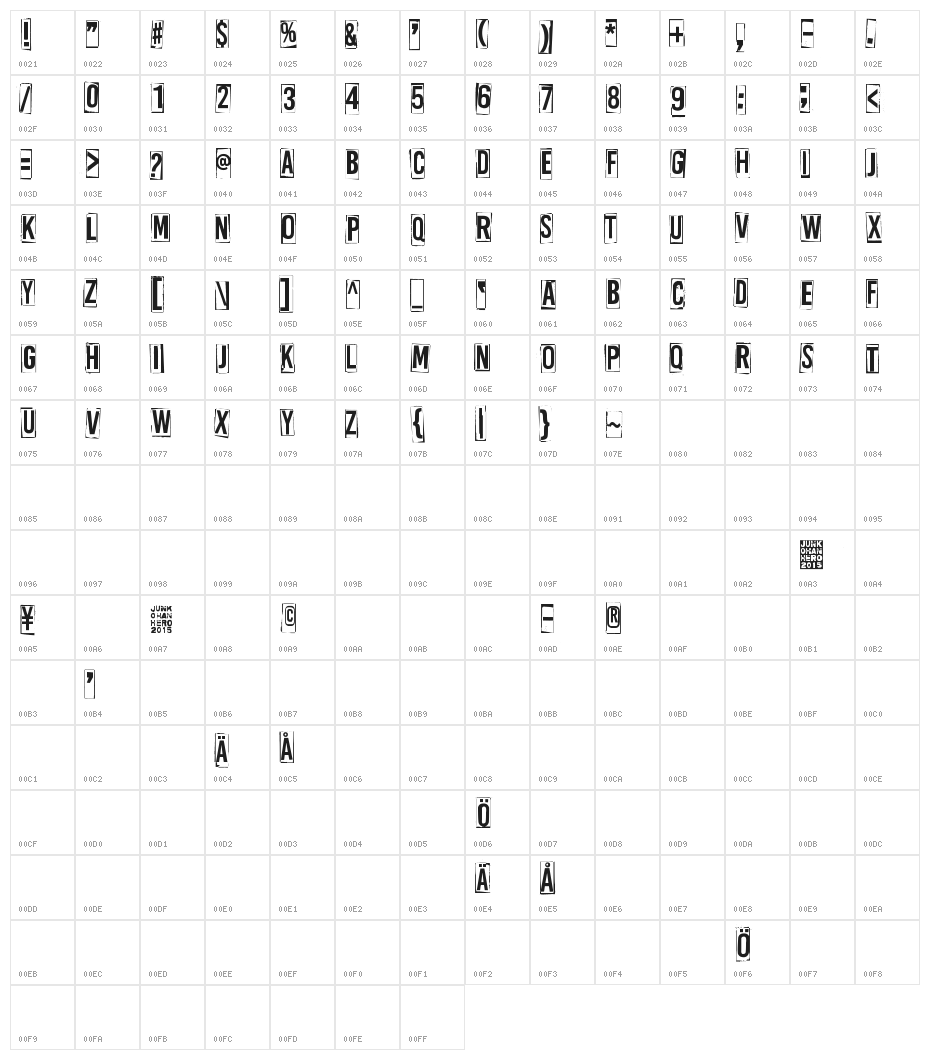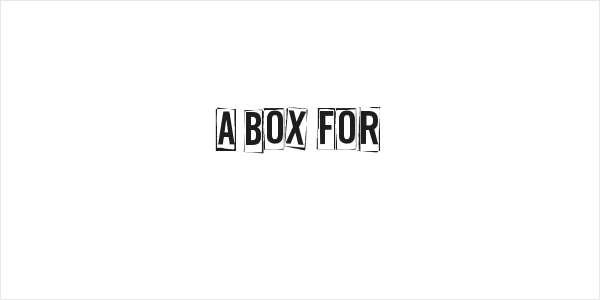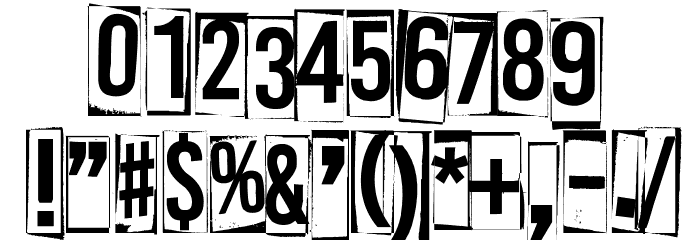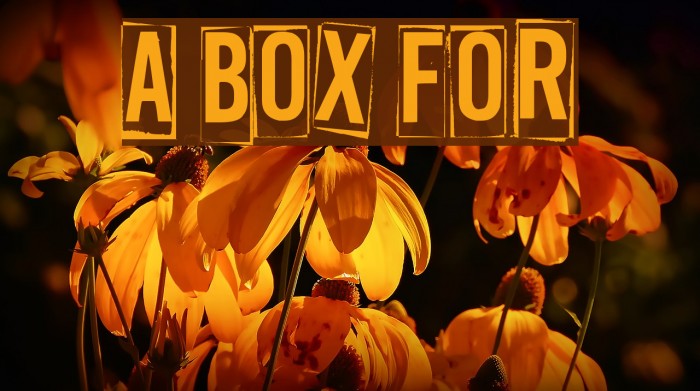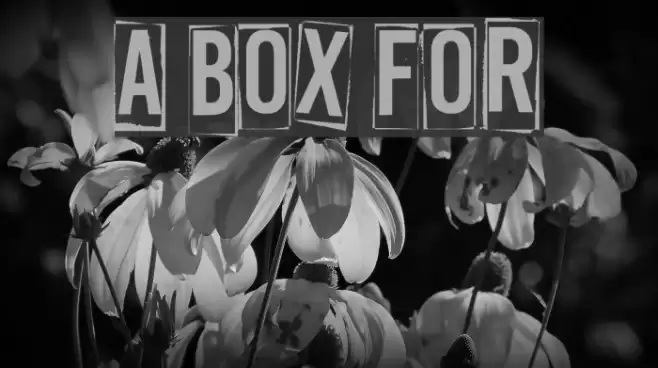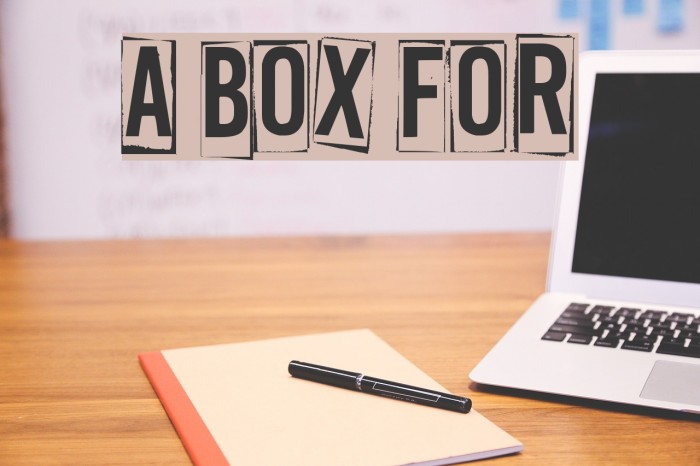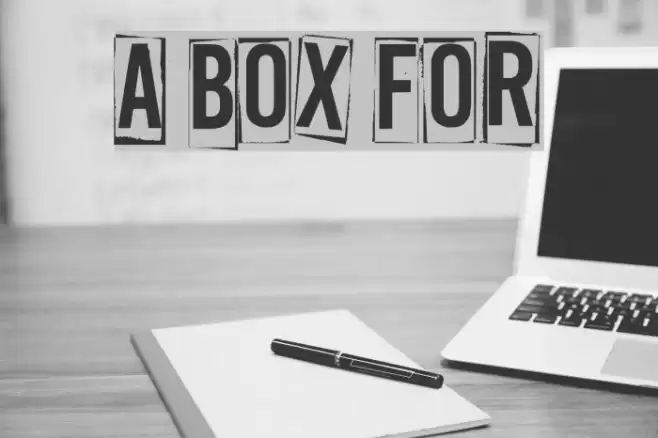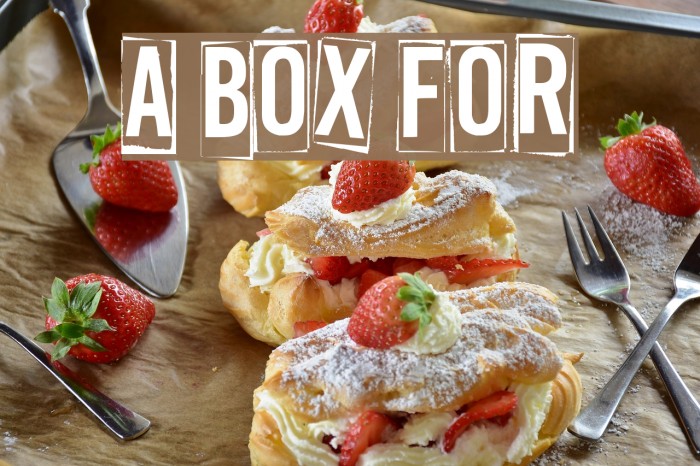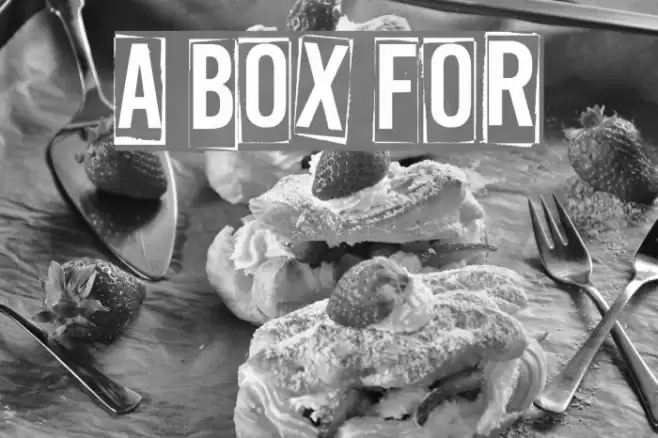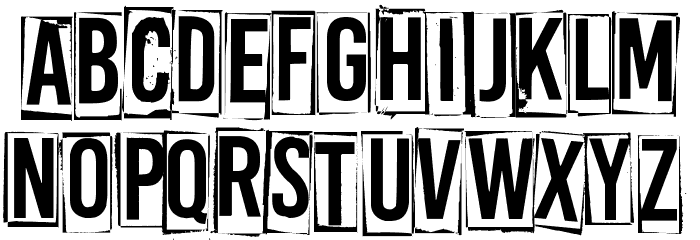
A Box For Font
✎ Distorted Eroded
| Категория | Distorted Eroded |
| Общий стиль | Vintage |
| Рекомендуемые проекты | Ideal for posters, album covers, branding for edgy or vintage-themed products, and any design needing a bold, impactful statement. |